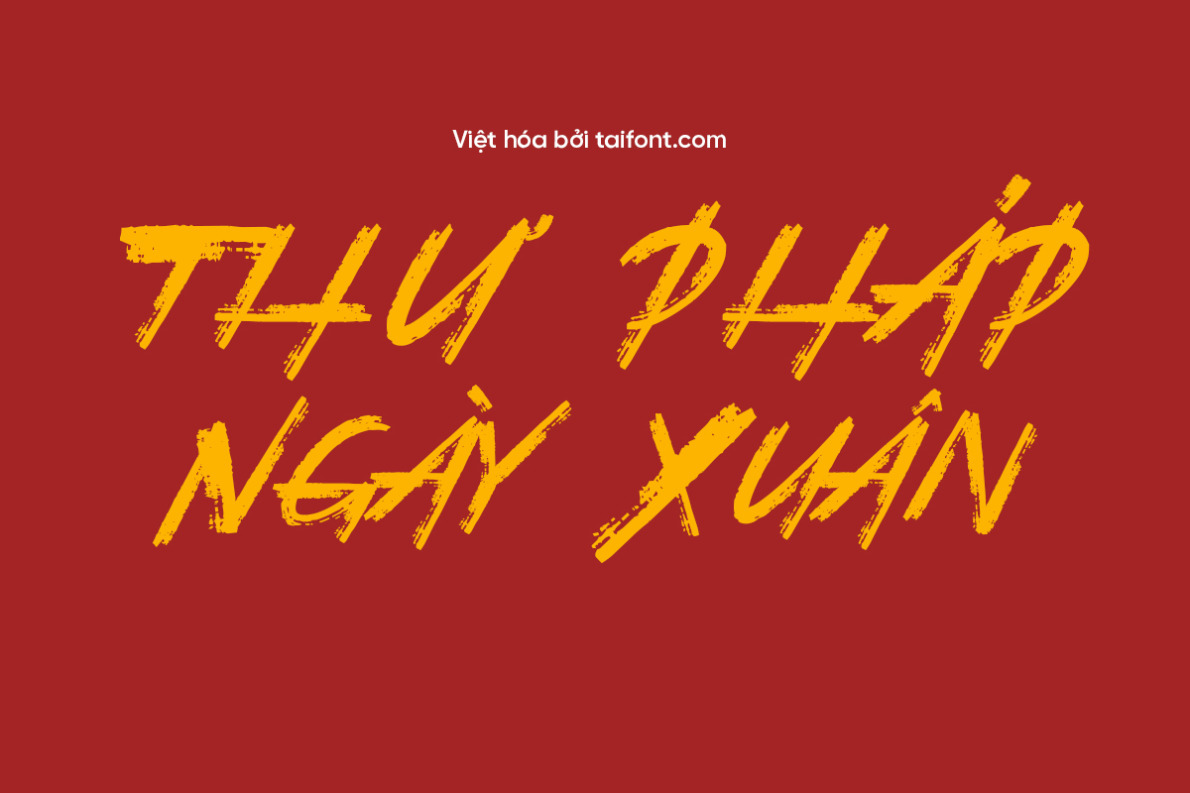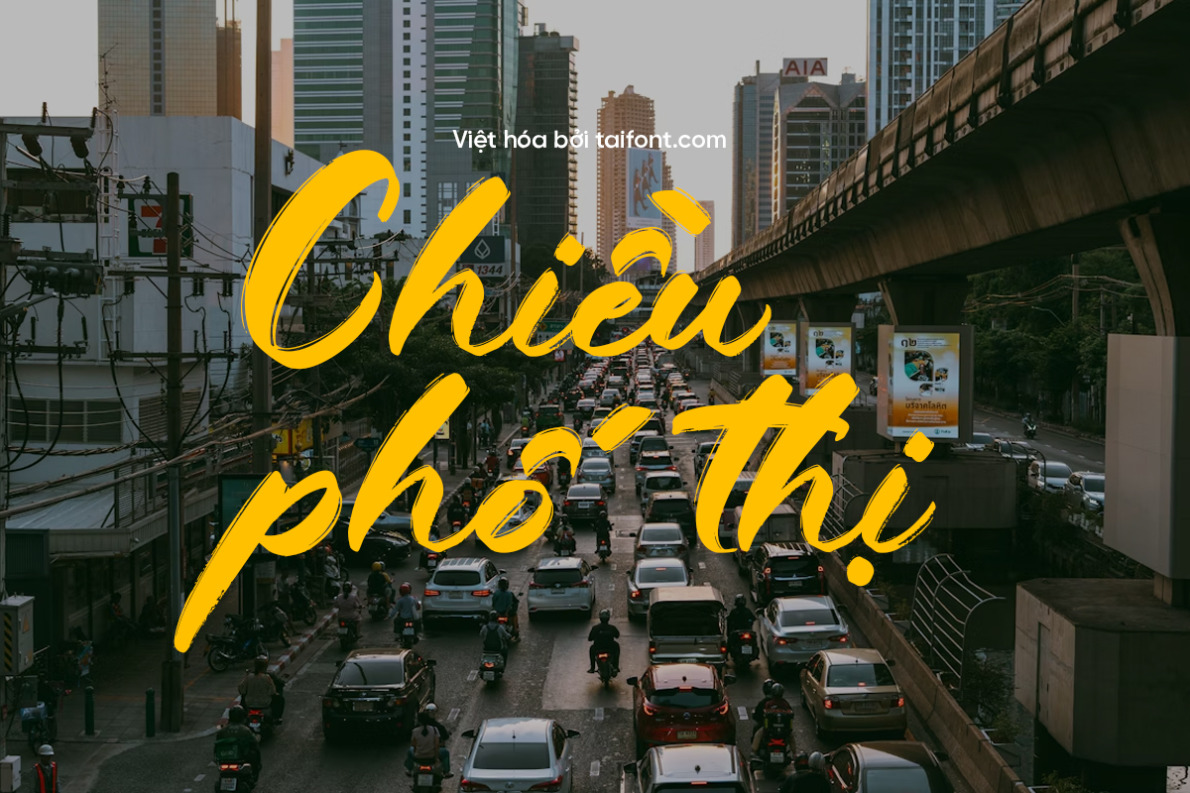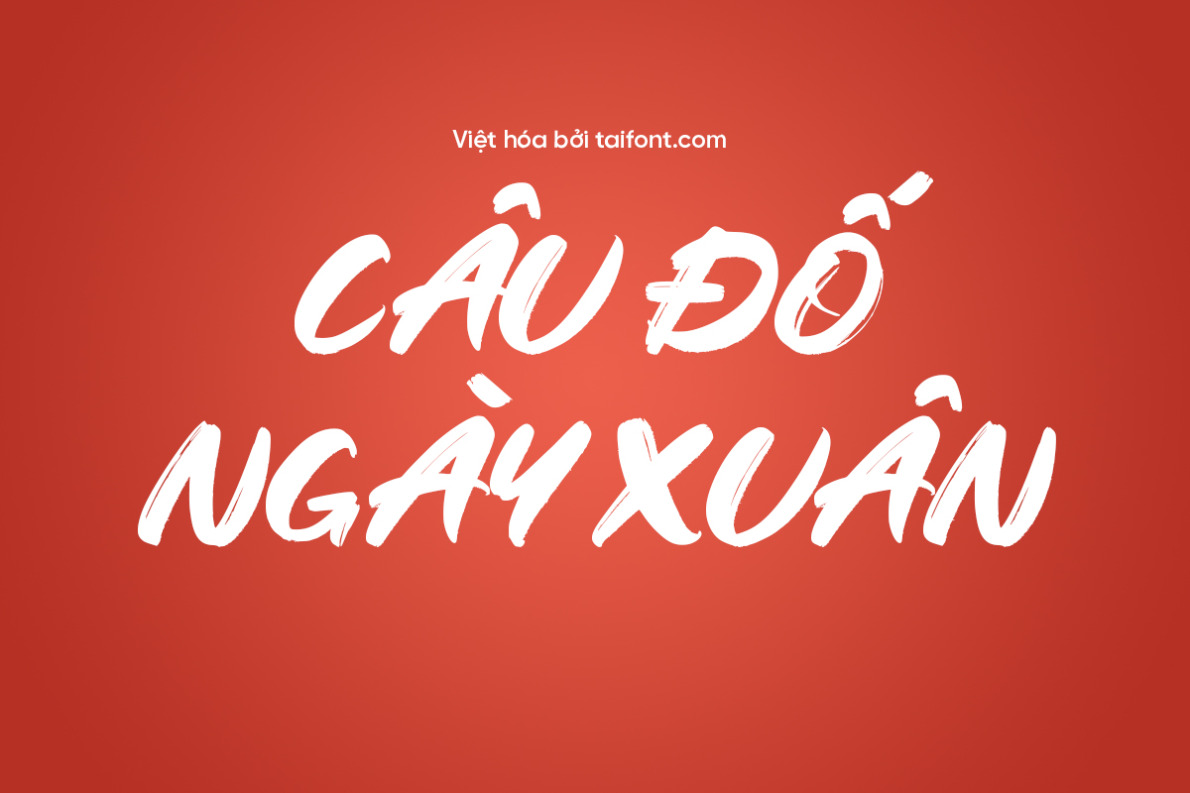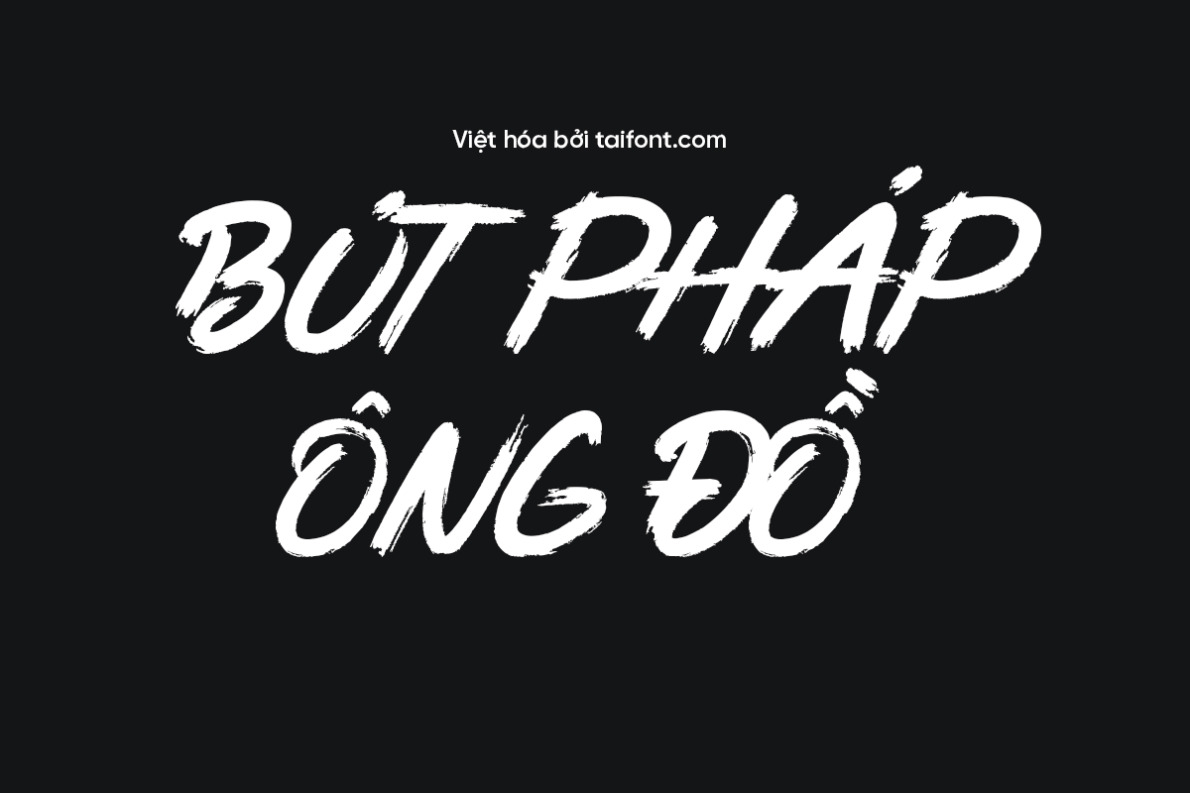
Tải Ngay! Top Font Thư Pháp Việt Hóa Đẹp Cho Mọi Thiết Kế
Bạn đang tìm kiếm những nét chữ mềm mại, bay bổng, mang đậm hồn Việt để thổi làn gió mới vào các dự án thiết kế của mình? Font thư pháp Việt hóa chính là chìa khóa! Không chỉ là những kiểu chữ đơn thuần, đây còn là sự kết hợp tinh tế giữa nghệ thuật thư pháp truyền thống và khả năng ứng dụng linh hoạt trong kỷ nguyên số.
Hiểu được mong muốn của các nhà thiết kế, người làm sáng tạo nội dung, hay đơn giản là những ai yêu thích vẻ đẹp của chữ viết, bài viết này sẽ tổng hợp và chia sẻ đến bạn những bộ font thư pháp Việt hóa đẹp nhất, ấn tượng nhất để bạn dễ dàng tải về và sử dụng.
Font Việt hóa TF Broken Horizon – Font thư pháp
TF Broken Horizon Việt hóa là một font chữ thư pháp brush (kiểu cọ vẽ) độc đáo, nổi bật với thiết kế mạnh mẽ, phóng khoáng và đầy cá tính. Font này gợi cảm giác như những nét bút lông dứt khoát, tự do nhưng vẫn mang đậm dấu ấn nghệ thuật, toát lên sự năng động, ấn tượng và một chút tinh nghịch, lý tưởng để tạo điểm nhấn nổi bật và thu hút mọi ánh nhìn, đặc biệt trong các dịp lễ hội.
Font Việt hóa TF Flashstrike – Font thư pháp
TF Flashstrike Việt hóa là một font chữ brush (kiểu cọ vẽ) độc đáo, mang phong cách thư pháp hiện đại và mạnh mẽ, nổi bật với việc chỉ có các ký tự hoa (uppercase). Font này gợi cảm giác về những nét cọ lướt nhanh, dứt khoát và đầy năng lượng, toát lên sự táo bạo, cá tính và ấn tượng mạnh mẽ, lý tưởng để tạo điểm nhấn nổi bật và thu hút mọi ánh nhìn trong các thiết kế đòi hỏi sự cá tính và phong cách nghệ thuật độc đáo.
Font Việt hóa TF Storm Wraith – Font thư pháp
TF Storm Wraith Việt hóa là một font chữ brush (kiểu cọ vẽ) độc đáo, nổi bật với thiết kế nét bút đậm, mạnh mẽ và đầy phóng khoáng, mang phong thái thư pháp hiện đại và đầy cá tính. Font này gợi cảm giác về những đường cọ lướt nhanh, dứt khoát và có hồn, toát lên sự năng động, ấn tượng và một chút bí ẩn, lý tưởng để tạo điểm nhấn mạnh mẽ và thu hút mọi ánh nhìn trong các thiết kế đòi hỏi sự táo bạo và phong cách nghệ thuật độc đáo.
Font Việt hóa TF Super Dash – Font Brush
TF Super Dash Việt hóa là một font chữ brush (kiểu cọ vẽ) độc đáo, nổi bật với thiết kế nét bút to lớn, mạnh mẽ và đầy phóng khoáng, gợi cảm giác về những đường cọ lướt nhanh, dứt khoát như những nét thư pháp hiện đại. Font này toát lên phong thái năng động, cá tính và đầy ấn tượng, lý tưởng để tạo điểm nhấn mạnh mẽ và thu hút mọi ánh nhìn trong các thiết kế đòi hỏi sự táo bạo và phong cách nghệ thuật độc đáo.
Font Việt hóa TF Neo Emotiost – Font thư pháp
TF Neo Emotiost Việt hóa là một font chữ kiểu brush (cọ vẽ) kết hợp phong cách thư pháp, nổi bật với vẻ đẹp nghệ thuật, bay bổng và đầy cảm xúc. Font này mang đến cảm giác như những nét vẽ tay được thực hiện một cách phóng khoáng, uyển chuyển nhưng vẫn rất có hồn và tinh tế, toát lên sự tự do, sáng tạo và một chút lãng mạn.
Hãy sẵn sàng khám phá kho tàng font chữ độc đáo này, từ những nét bút thanh thoát, uyển chuyển cho đến những kiểu chữ mạnh mẽ, cá tính